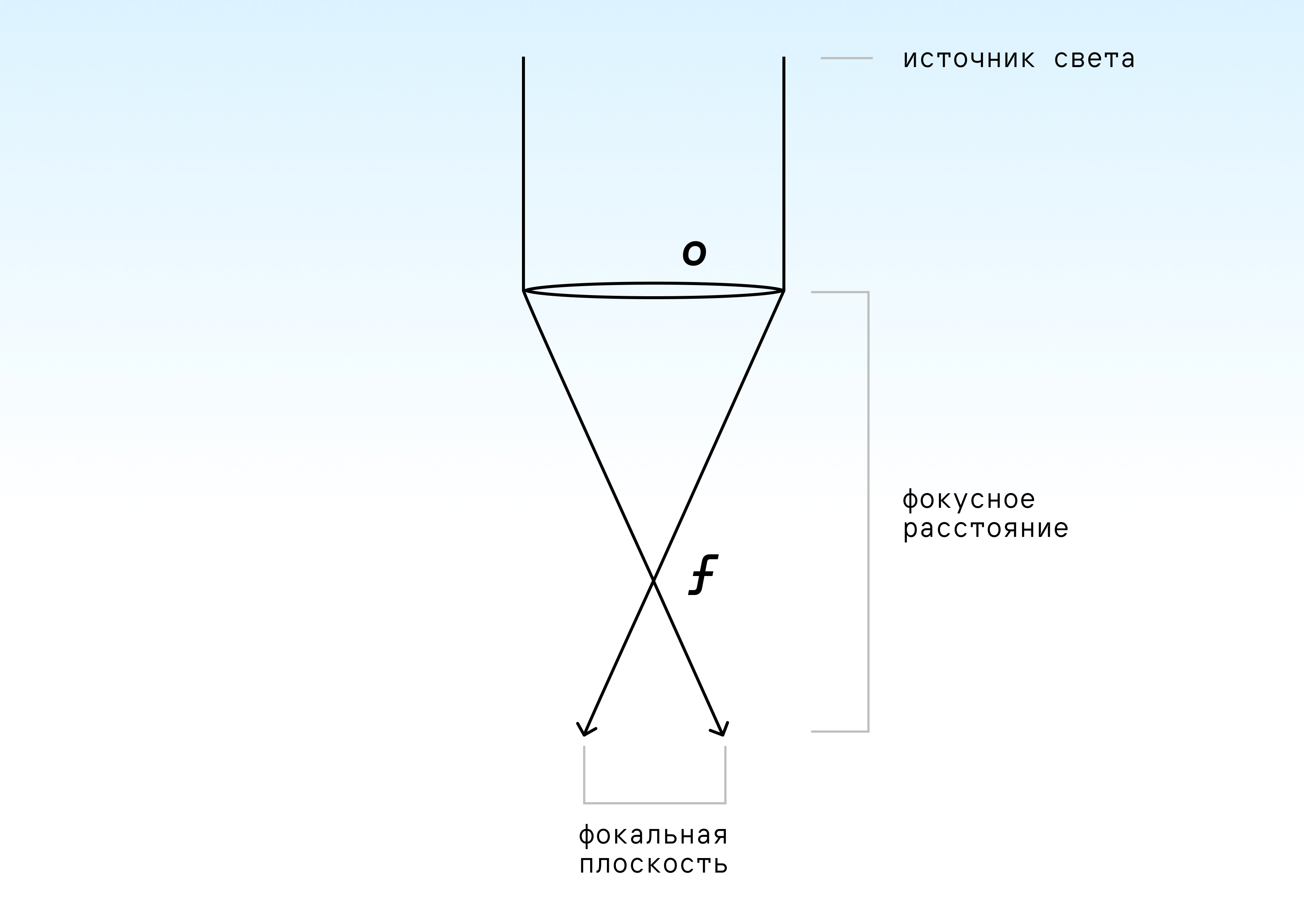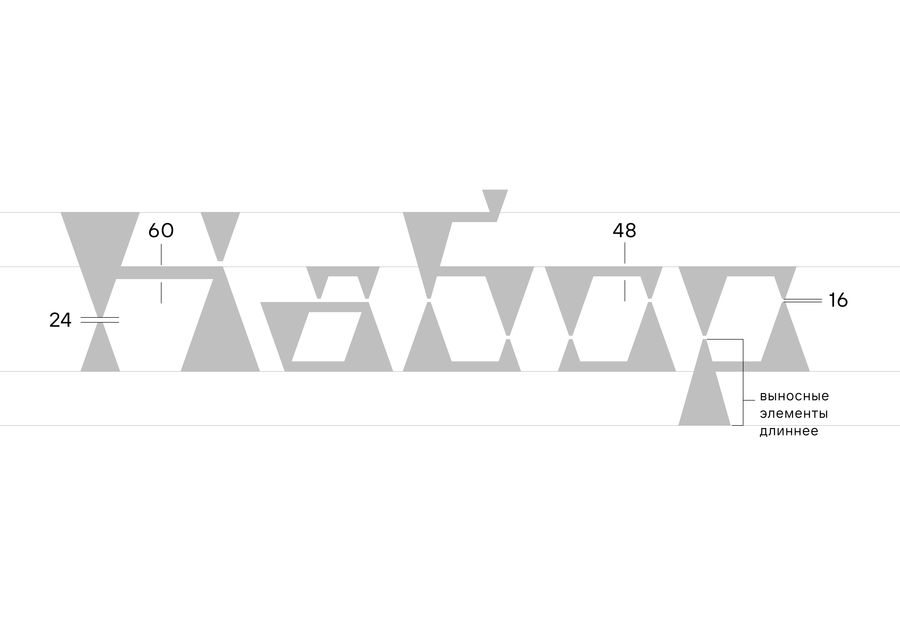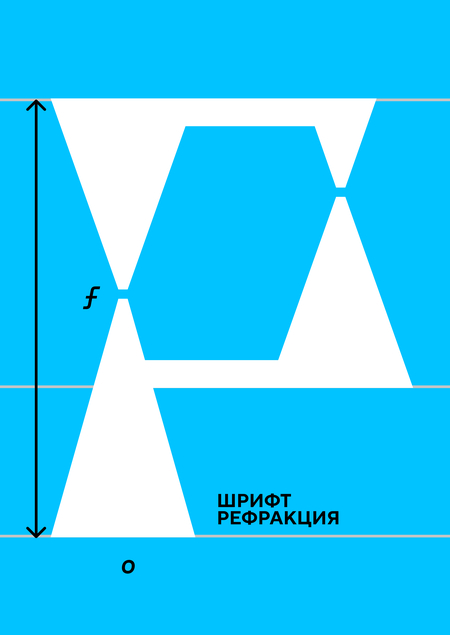
Рефракция шрифт
Шрифтовая система, где каждая буква возникает не как статичная форма, а как процесс преломления света. Буквы не «нарисованы», а «спроецированы» через призму оптических законов. Шрифт является модульным и несет в себе техничный и современный характер.
Бренд стеклянной граненой посуды, преимущественно для коктейлей